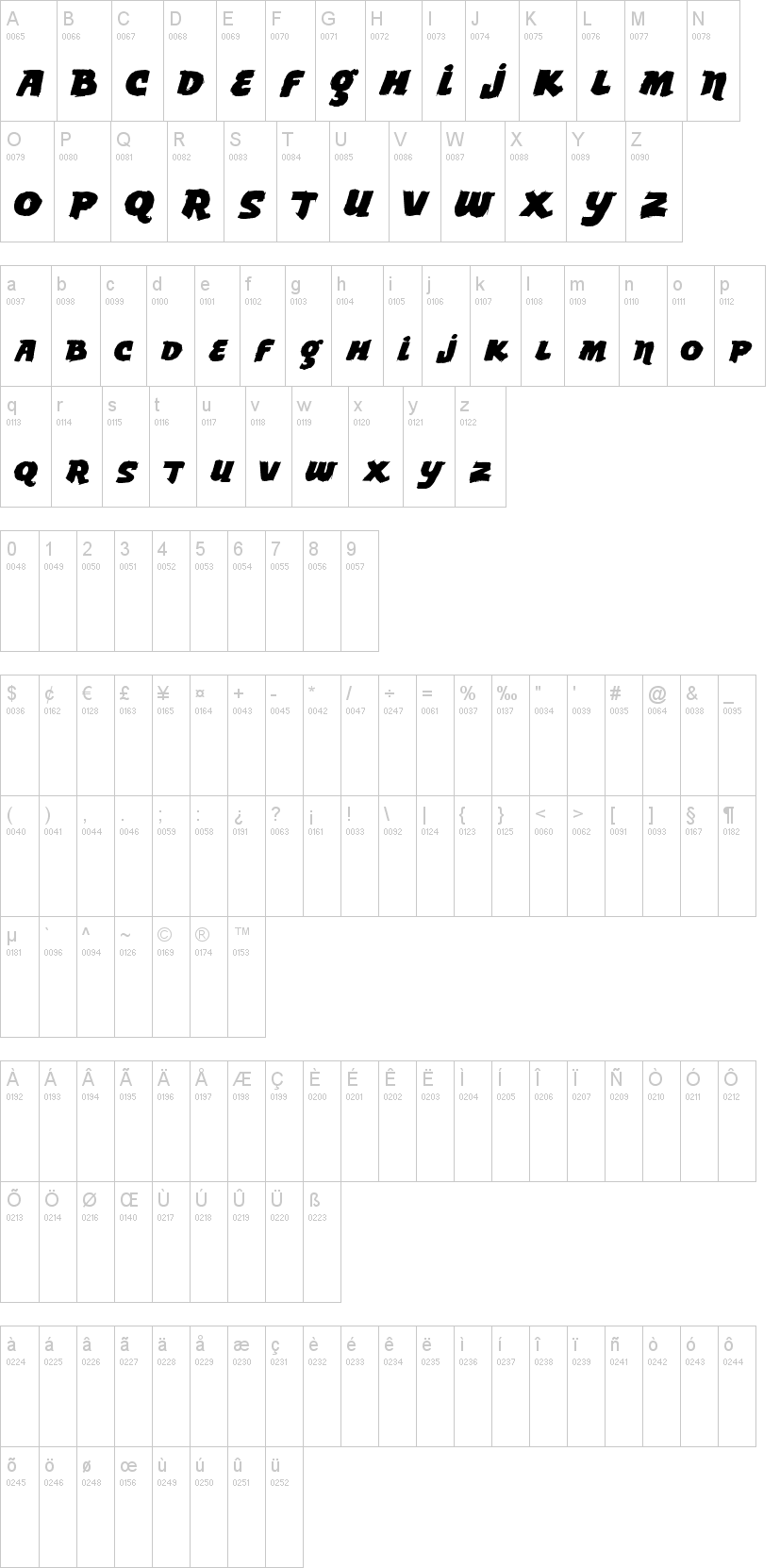
Vtks Lemon Drop是一种非常有趣的字体,它的设计灵感来自于柠檬糖果。这款字体的特点是线条简单、流畅,充满了活力和趣味性。它的字母形状有些奇特,带有一些圆润和弧度,整体看上去非常鲜艳明亮。 这种字体非常适合一些需要突出个性、趣味性、年轻化的设计场景,比如柠檬糖果品牌的logo设计、儿童读物或玩具的设计等。在印刷品或平面设计中,使用Vtks Lemon Drop可以给人带来一种欢快、轻松、愉悦的感觉。内容介绍
Vtks Lemon Drop是一款非常不错的手写艺术字体,具有很好的视觉感,适合于文化类的宣传设计、商业类品牌的广告和产品包装设计以及个性化文字排版等较多场景。